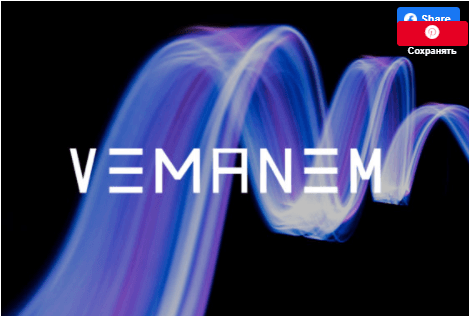
Vemanem Font
Vemanem — современный и классный дисплейный шрифт. Независимо от темы, этот шрифт станет невероятным активом в вашей библиотеке шрифтов, поскольку он может поднять любое творение на новый уровень.